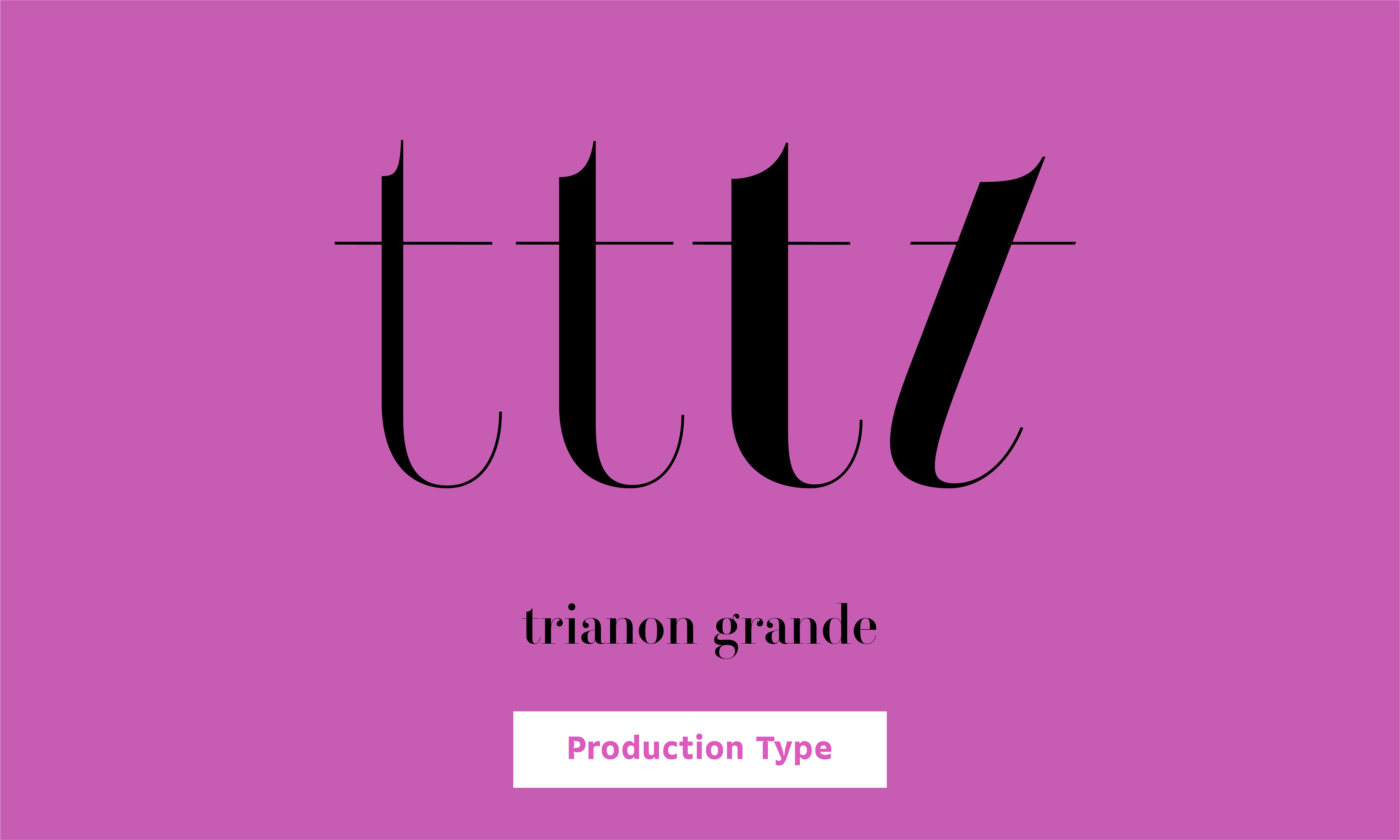
- Trianon은 패션잡지나 명품브랜드에서 자주 사용하는 Didot과 유사하지만 화려한 장식보다는 리듬과 가독성 등에 보다 집중한 폰트이다.
Trinon Display와 Grande는 특히 기존의 Didot과 유사하게 화려한 장식과 명백히 대조적인 인상으로 디자인 되었다.
폰트 정보 폰트명 Trianon Grande 구분 명조 폰트디자인 Loïc Sander, Sandra Carrera, Roxane Gataud, Yoann Minet